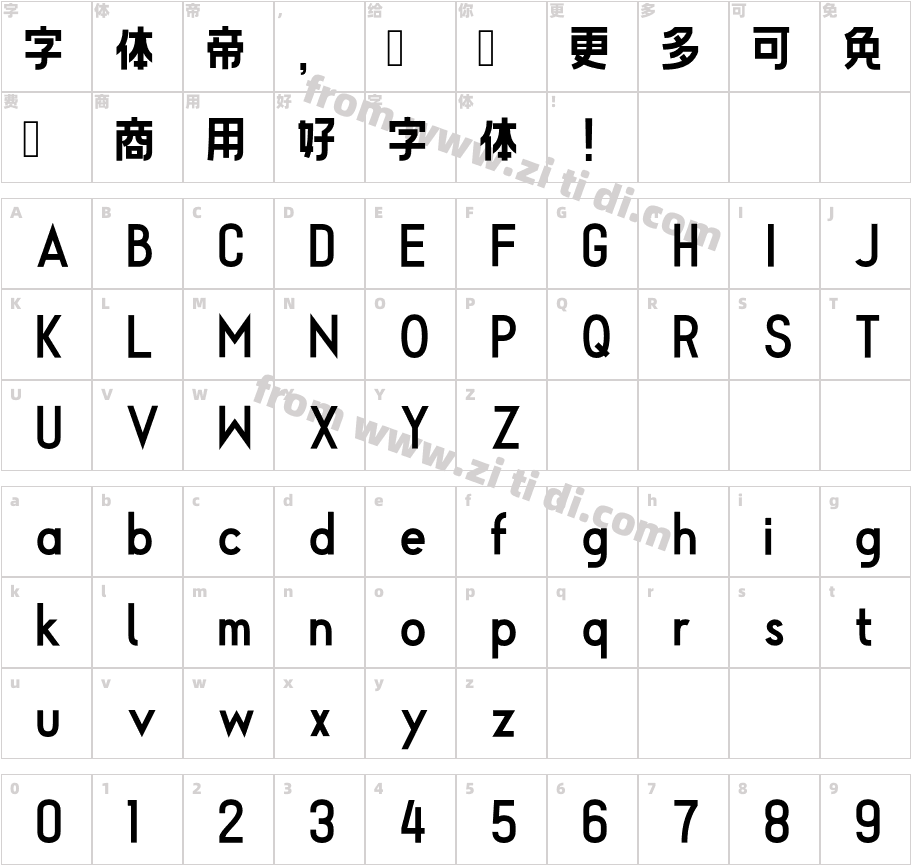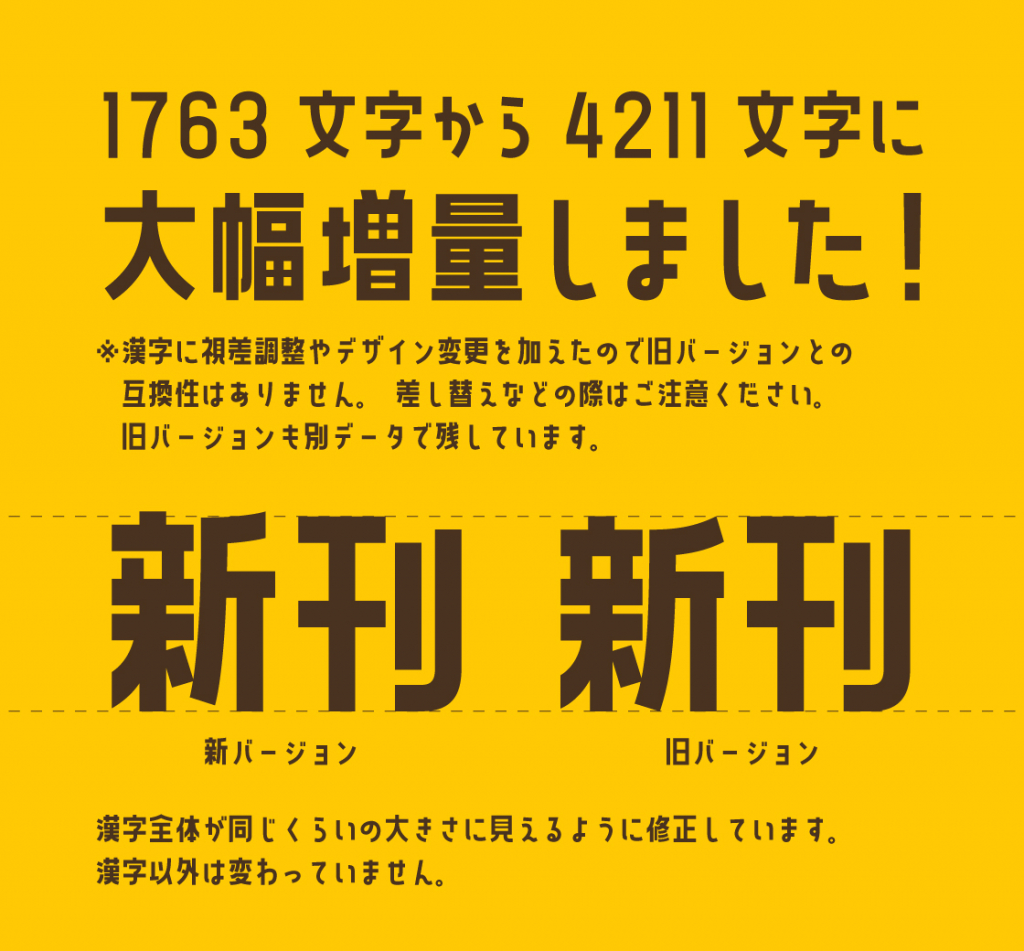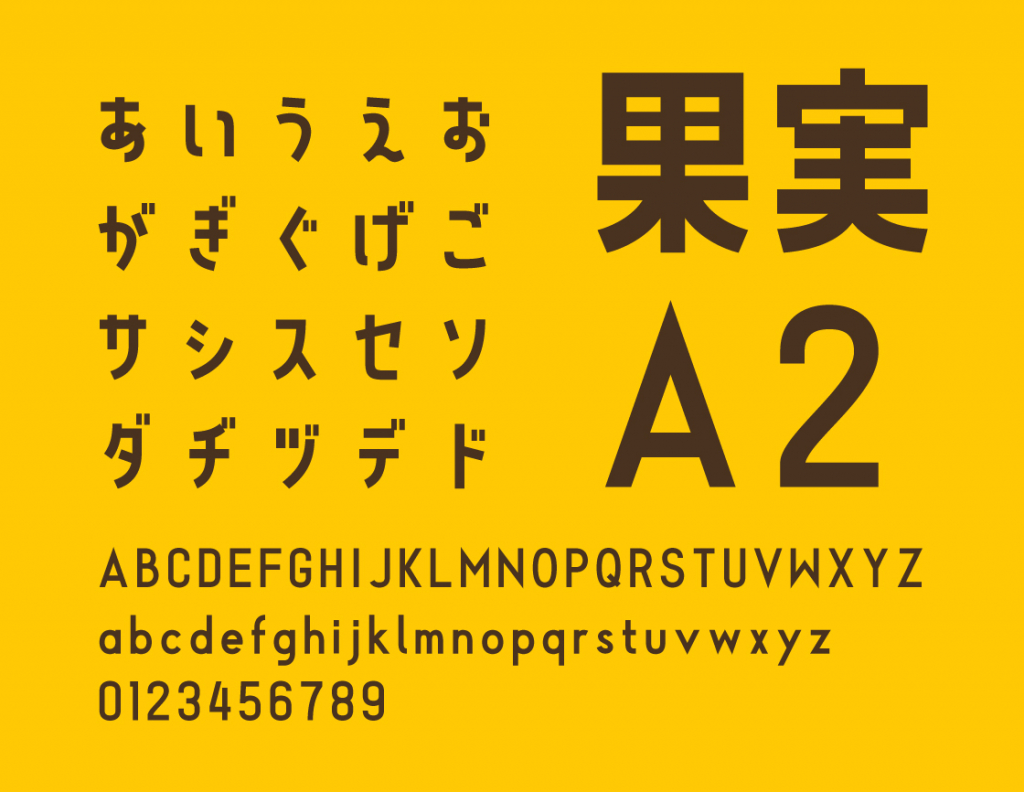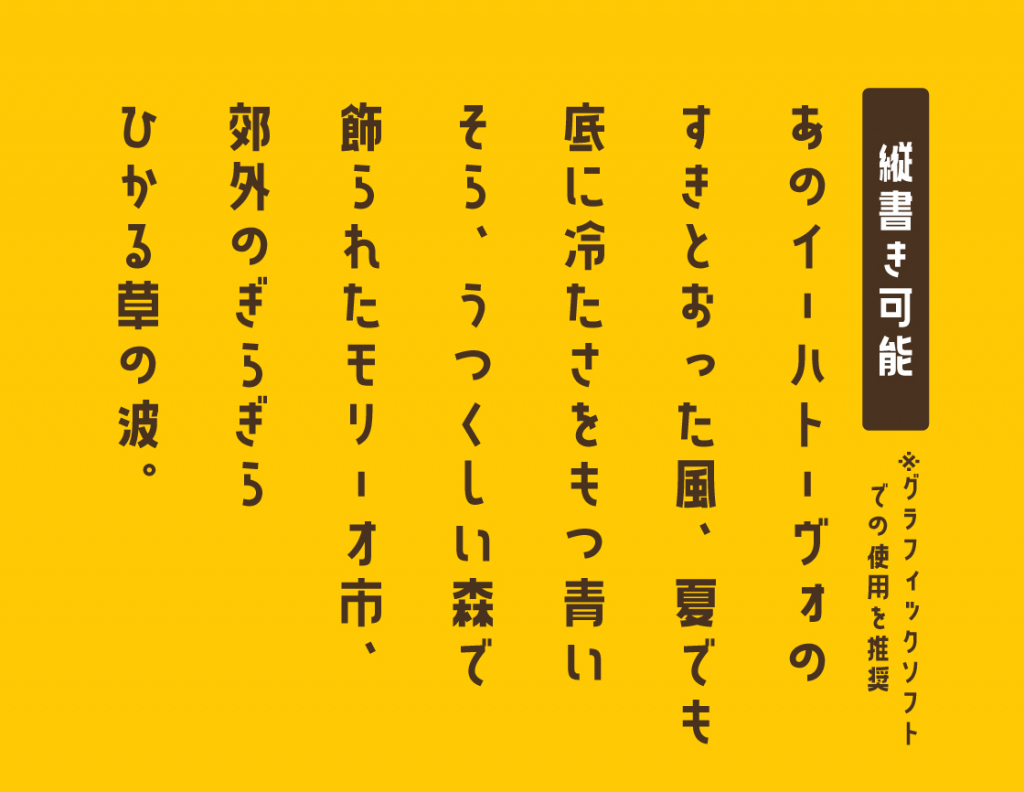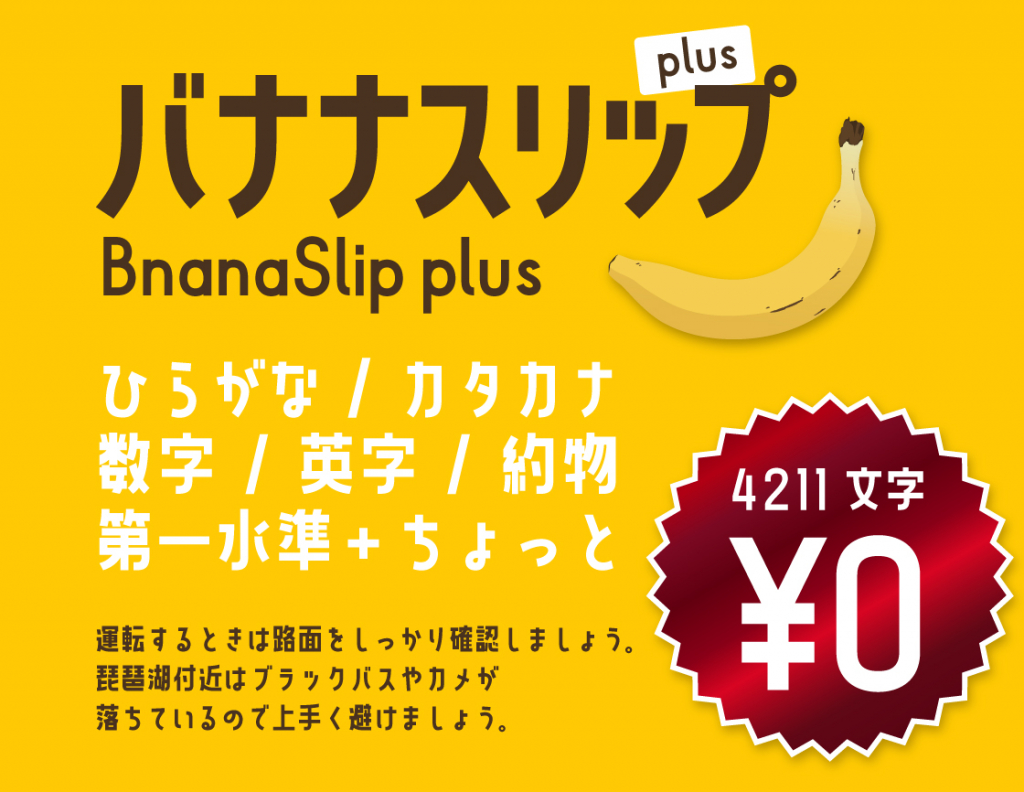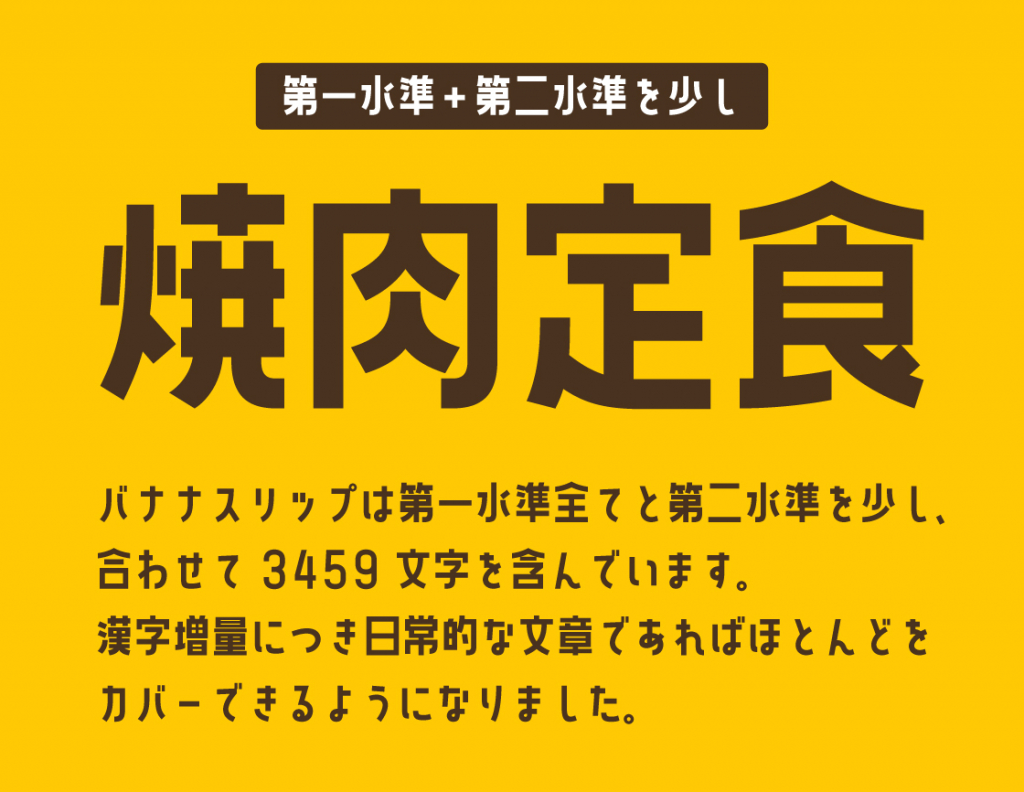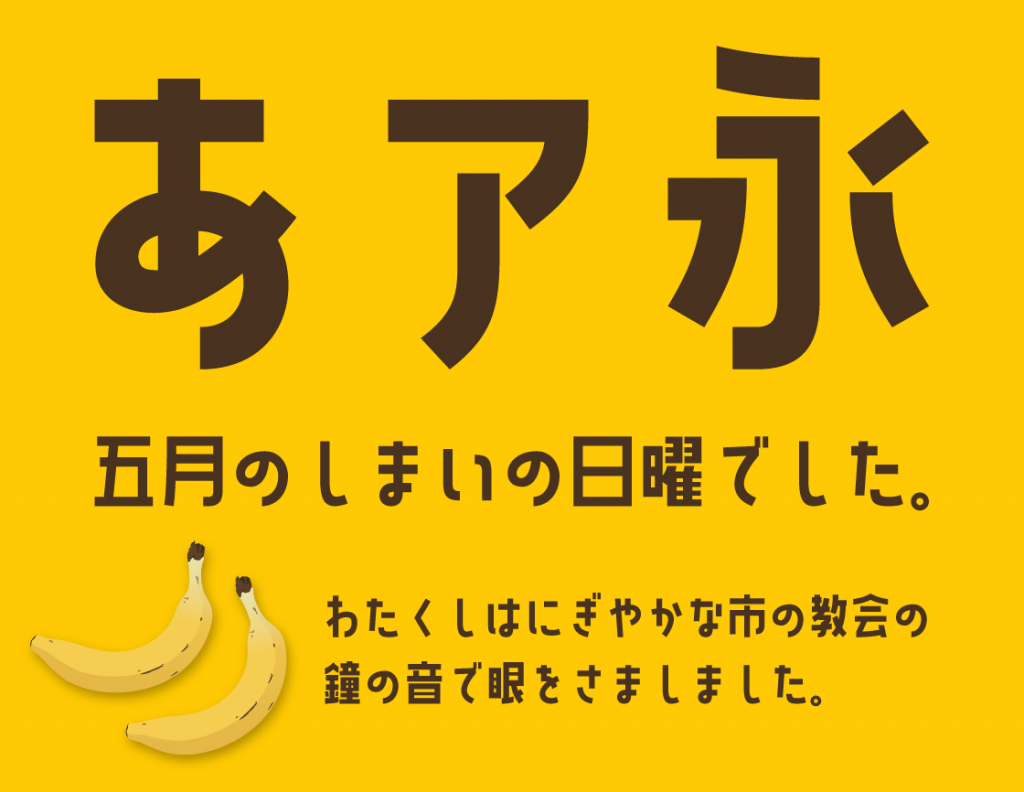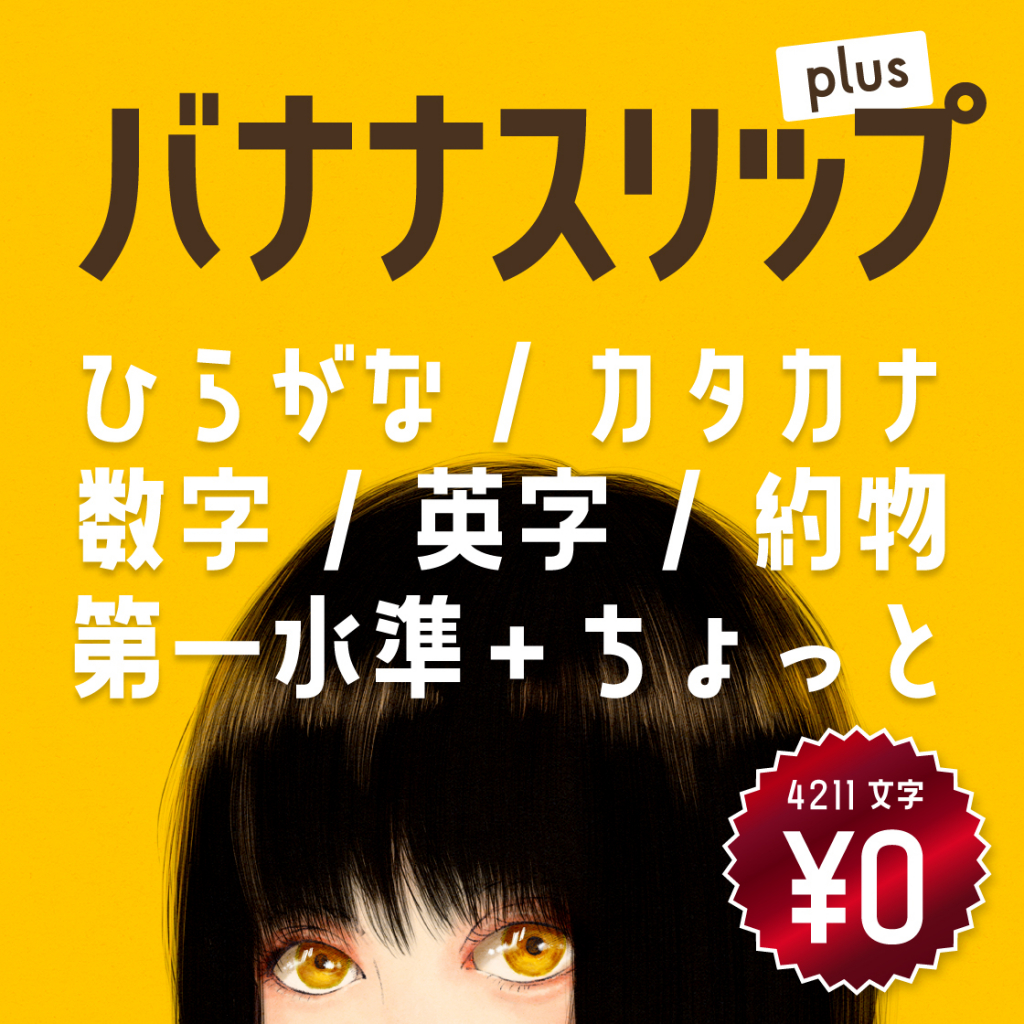
香蕉Plus字体
字体风格: 个性
香蕉Plus是一种以香蕉为灵感而创建的,更加简明现代化的字体。新版本对汉字进行了视差调整和设计更改。字体整体已被修改,使其看起来与 Ui 大小相同。
平假名、片假名、字母数字字符、一些符号、汉字(第一级 + 第二级部分 + α 3459 个字符)
记录了 4211 个字符